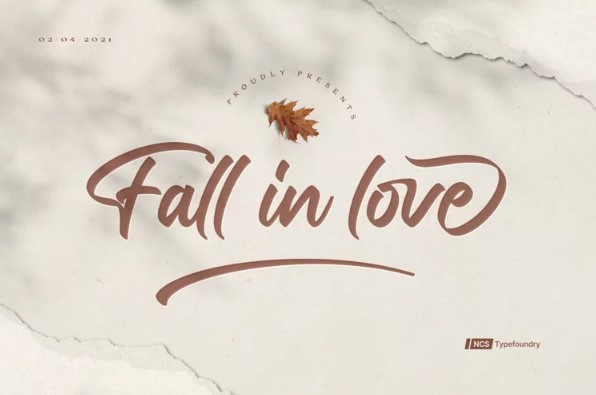
[Fontbundles] Fall in love Font
Смелый и стильный каллиграфический шрифт с современным штрихом дарит аутентичный, харизматичный и уверенный в себе выбор шрифта для целого ряда дизайнерских проектов. Например, логотип, дизайн футболок, упаковка продукции, стильная подпись, бизнес-брендинг и промо-кампажин. Добавьте его к вашим самым креативным идеям и заметьте, как он делает их живыми! Влюбитесь в его невероятно выразительный и неподвластный времени стиль и используйте его для создания эффектных дизайнов!